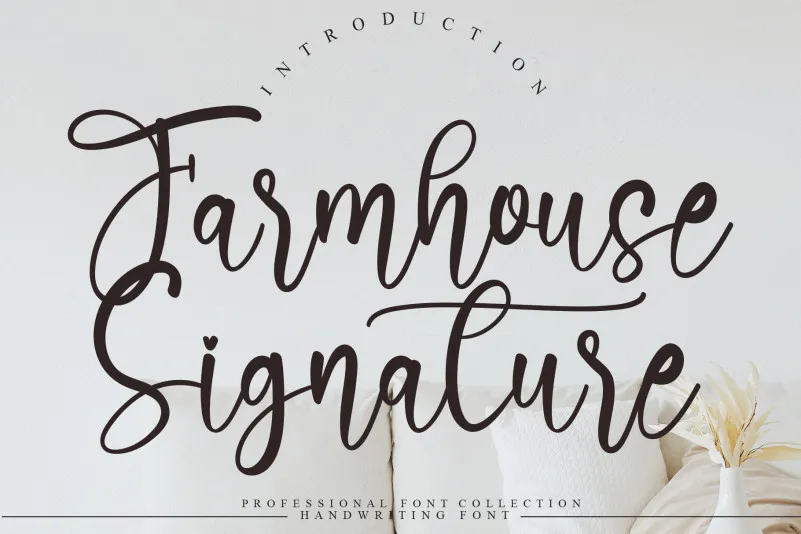
Farmhouse Signature Script Font – Download Grátis
Esta font ‘Farmhouse Signature Script Font’ é uma criação especial para designers amadores e profissionais que buscam uma maneira única de personalizar seus projetos gráficos. Com seu traço fluido e natural, esta font traz um toque de rusticidade e autenticidade às suas páginas digitais. Combinando elementos delicados e fortes em sua tipografia, a ‘Farmhouse Signature Script Font’ é ideal para designers que desejam dar vida aos seus projetos, adicionando uma personalização única. Perfeita tanto para texturas legíveis quanto para títulos chamativos, esta font não apenas deixa seu projeto com um toque autêntico e encantador, mas também oferece a oportunidade de incluir uma marca pessoal ou familiar no design. Seja em logotipos, cards de visita, cartazes ou até mesmo em mensagens de texto personalizadas, a ‘Farmhouse Signature Script Font’ proporciona um contraste perfeito entre a elegância de uma fonte de签字脚本和天然的田园风格带来的原始感。流畅而自然的设计使这个字体成为你项目中独特体验的一部分。 无论是用于文本阅读还是标题吸引人,这款‘Farmhouse Signature Script Font’都能为你的设计增添一抹独特的色彩。不论是个人使用还是专业应用,它都是一个完美的选择,能够让你的作品更加生动和个性化。